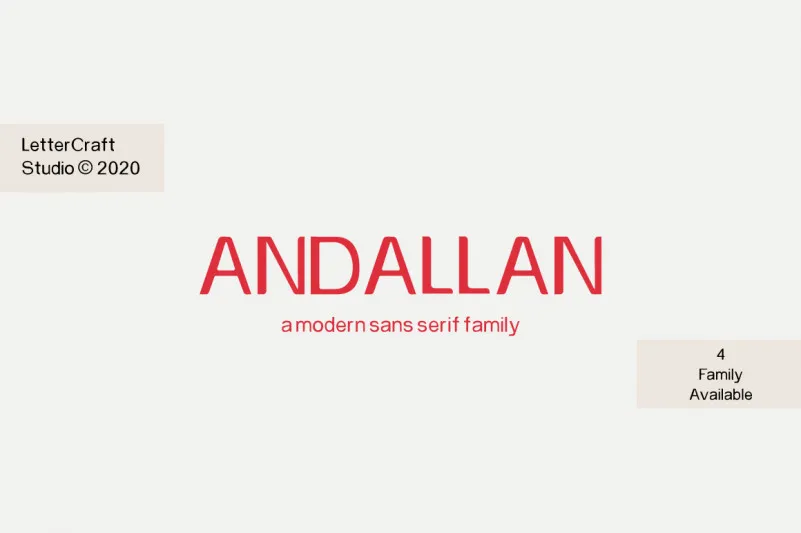
Andallan Font – Fonte Grátis
Andallan Font
A Andallan Font é uma elegante escolha para quem busca um estilo moderno e claramente legível. Este novo lançamento da LetterCraft Studio faz parte do rico catálogo de fontes sans-serif, com seu próprio charme distintivo que combina simplicidade e força. Como a sua herança mais conhecida, o ‘Tulehu’, esta nova fonte oferece uma experiência de design limpa e versátil, projetada para se adaptar em diversas aplicações, seja em logotipos ou gráficos de web, garantindo sempre um alto nível de legibilidade. Uma das principais vantagens desta fonte é sua capacidade de criar um impacto forte e contemporâneo em qualquer design que use, sem abrir mão de uma aparência suave e agradável. Ainda não experimentou? Quem sabe você possa descobrir qual é o seu papel perfeito no seu próximo projeto visual?